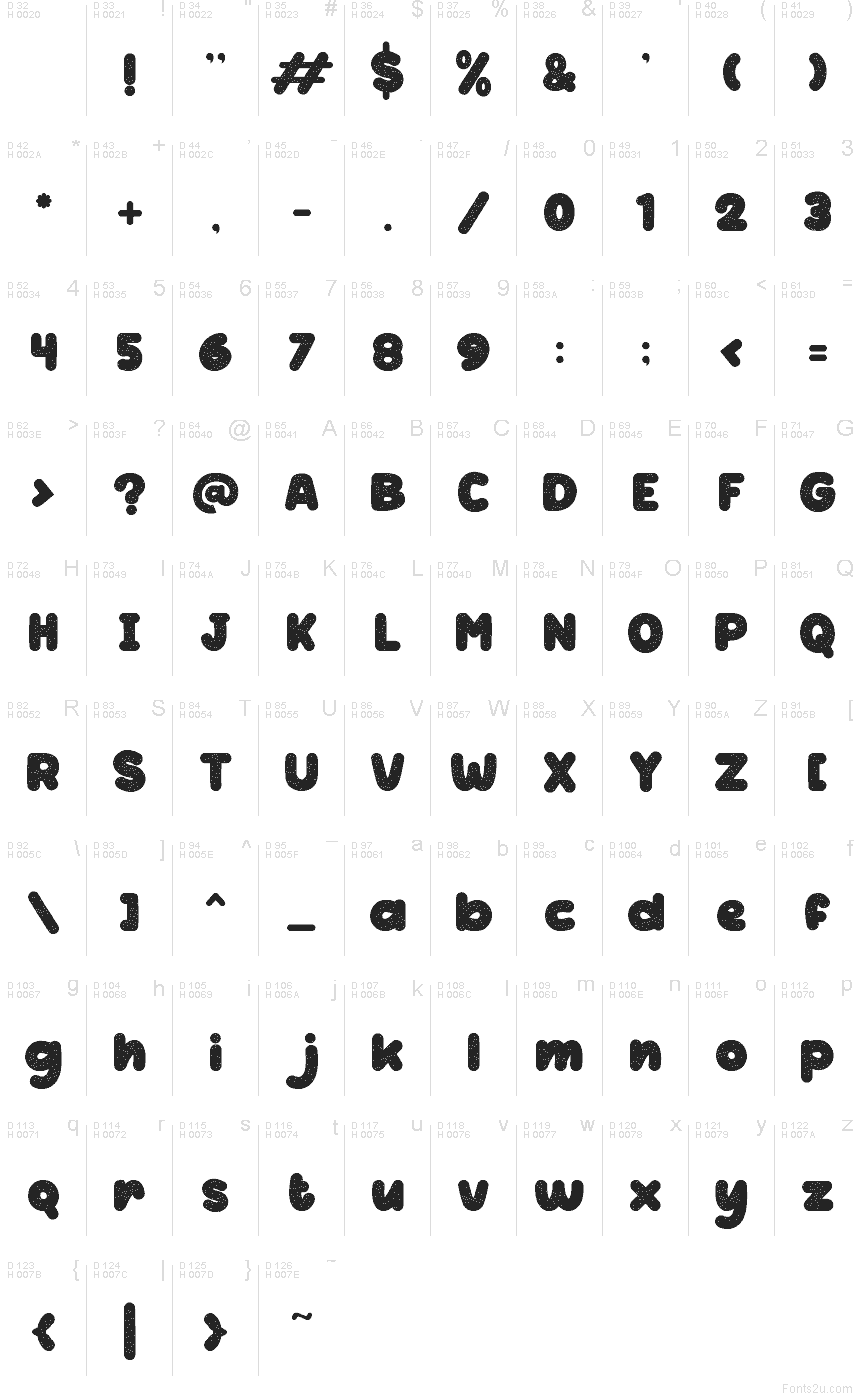
Smoky Maple One od Putracetol Studio to darmowy font display w stylu cartoon, wyróżniający się pulchnymi, pełnymi życia literami oraz zabawnym, odręcznym charakterem. Zaokrąglone kształty są miękkie i wyraziste, a kreskowana tekstura wewnątrz każdej litery nadaje całości nakrapianą, niemal puszystą powierzchnię, dzięki czemu projekt nie wydaje się płaski.
Idealnie sprawdza się na opakowaniach dla dzieci, w brandingu słodyczy czy przekąsek, na tytułach plakatów, w miniaturkach na YouTube czy na okładkach, gdzie czcionka ma od pierwszego wejrzenia budzić sympatię. Dzięki swoim wydatnym i niemal wyczuwalnym w dotyku kształtom, świetnie nadaje się również do krótkich logotypów, zaproszeń na przyjęcia i nagłówków, które mają mieć przytulny i nieco figlarny wydźwięk.
Smoky Maple One